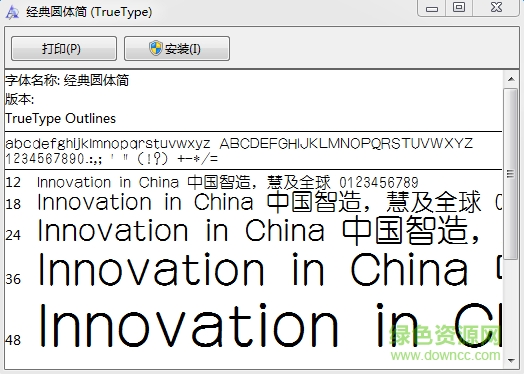
軟件介紹 軟件標簽: 經典字體 字體 經典圓體簡是一款很實用的電腦簡體字體,這款字體因為其俊秀、大氣,而且工整有規(guī)范的特點被很多人喜歡,也正是因為有很多朋友在找這款字體,所以小編才為大家收集好了,歡迎大家來綠色資源網下載。安裝說明:第一種1.下載字體并解壓縮;2.開始中打開控制面板;3.在控制面板中打開字體文件夾;4.把下載的字體復制到此文件夾下;5.文字添加完成第二種1.下載字體并解壓縮;2.把文件根目錄下的字體壓縮包解壓縮;3.把文件根目錄下的安裝字體.bat放到含有字體文件的文件夾中,雙擊安裝字體.bat軟件;4.文字添加完成 軟件截圖 上一張下一張(1 / 1) 安裝詳細截圖 猜你喜歡 經典字體 經典字體 綠色資源網小編為大家收集了經典字體的各種書體,比如經典綜藝體簡體,這種經典字體的整個字體效果還具有卡通元素;經典黑體簡是一款典型的簡體字體,是現(xiàn)代中文的一種標準化寫法,與繁體中文(又稱正體中文)相對等等,還有經典細宋簡、經典毛筆字體、經典繁淡古...,這一類字體在廣告設計、平面設計、學習等都有廣泛的應用,一次性給大家收集了,這樣大家用起來就方便多了。 查看更多>> 經典篆刻字體 2.14M/中文/5.0/下載 經典繁超黑 regular 1.17M/中文/5.0/下載 經典簡圓藝 2.44M/中文/5.0/下載 經典簡超宋 1.81M/中文/6.6/下載 經典簡方新 1.17M/中文/5.0/下載 簡圓新字體 1.95M/中文/5.0/下載 其他版本下載 標題 大小 更新日期 下載 下載地址 電腦版 經典圓體簡 點擊報錯 軟件無法下載或下載后無法使用,請點擊報錯,謝謝! 關閉報錯反饋 請描述您所遇到的錯誤,我們將盡快予以修正,謝謝! *必填項,請輸入內容 本類最新 經典繁方新 緇忓吀緇嗗渾綆 regutar 94款經典字體打包 免費版 經典行書簡 經典圖案字字體 經典特宋簡體 相關文章 Photoshop字體安裝使用方法和技巧 如何解決“無法新增字體”問題 Win 7系統(tǒng)安裝字體方法 網頁字體大小設置方法 怎么改網頁字體大小 在Linux系統(tǒng)中安裝字體的幾種方法 windows7字體顯示問題:打開某些程序的時候顯示的是亂碼 用戶評論 熱門評論 最新評論 發(fā)表評論 查看所有評論(0) 昵稱: 請不要評論無意義或臟話,我們所有評論會有人工審核. 字數: 0/500 (您的評論需要經過審核才能顯示)